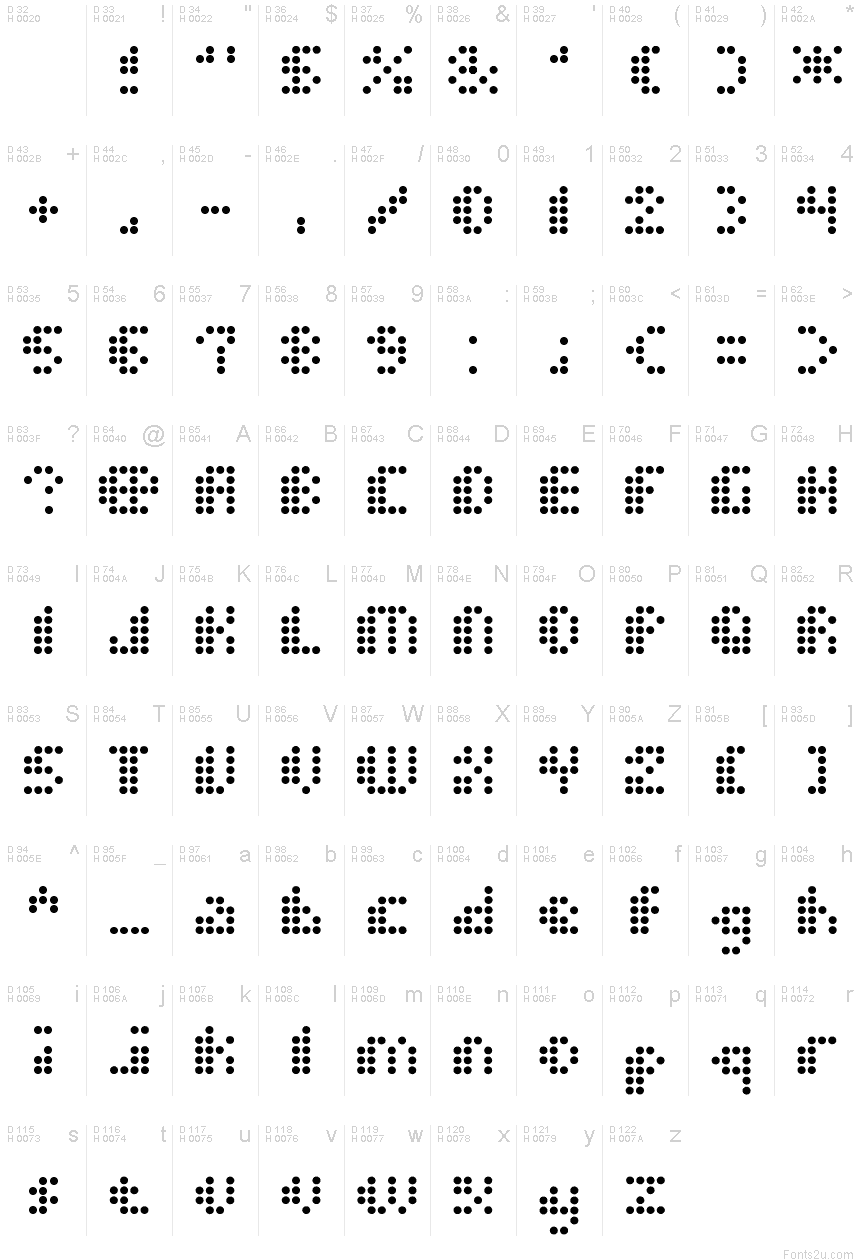
Dot Short of a Matrix di Smoking Drum è un carattere display digitale gratuito. Composto da griglie fitte di cerchi neri intensi, richiama i vecchi pannelli LED e i terminali sci-fi, mantenendo al contempo un aspetto nitido e tattile sullo schermo. Le lettere sono ben leggibili, ma conservano quel pizzico di astrazione che le fa sembrare codificate, come un messaggio segreto che pulsa su un display.
Usa Dot Short of a Matrix per dare carattere a poster techno, flyer per club, copertine di album sperimentali, titoli di giochi arcade, badge di interfaccia e branding futuristico. Il ritmo dei punti crea una forte texture visiva che risalta nelle grandi dimensioni e negli schemi cromatici ad alto contrasto. Per un miglior equilibrio, abbina questo font gratuito a un carattere sans serif geometrico semplice e di dimensioni ridotte come testo di supporto.